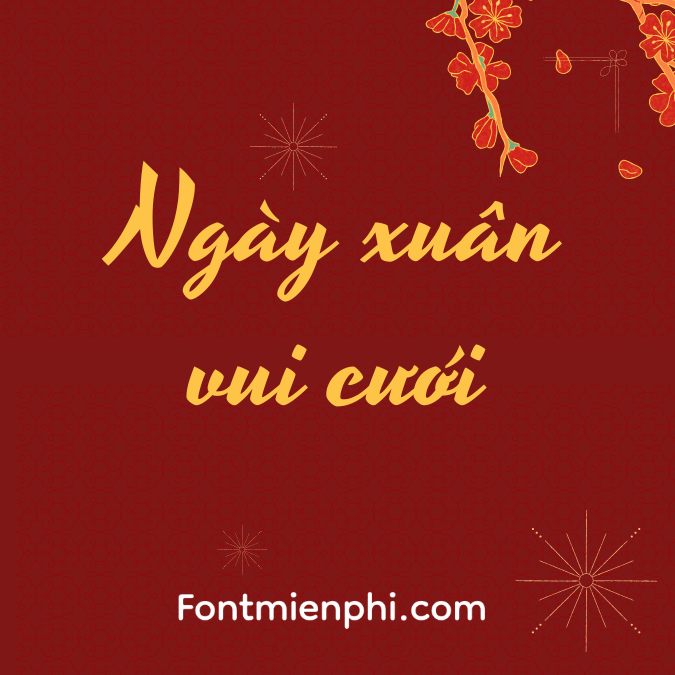
Font Việt hóa 1FTV VIP Yesteryear ,font Việt hóa tết
Font Việt Hóa 1FTV VIP Yesteryear – “Hoài Niệm Phong Hoa”
Phong cách độc đáo:
• Retro sang trọng: Lấy cảm hứng từ typography thập niên 60-70, nét thanh mảnh pha chút vintage, phù hợp thiết kế cổ điển nhưng vẫn giữ nét hiện đại.
• Tối ưu hóa tiếng Việt: Hỗ trợ đầy đủ dấu, bộ ký tự Unicode, đọc mượt ở mọi kích thước.
• Đậm chất nghệ thuật: Nét chữ uốn lượn nhẹ nhàng, điểm xuyến họa tiết hoa văn mềm mại (lá lúa, sóng nước) – đặc biệt trong bản VIP Pro.
Ứng dụng “đắt giá”:
• Nhận diện thương hiệu (quán café vintage, nhà hàng Pháp, thời trang retro).
• Thiệp mời, menu sang trọng, bao bì mỹ phẩm cao cấp.
• Album ảnh cưới, poster phim hoài niệm, tạp chí nghệ thuật.
Phiên bản đặc biệt:
VIP Pro: Bao gồm 3 biến thể (Regular, Italic, Shadow) + bộ vector họa tiết trang trí đi kèm.